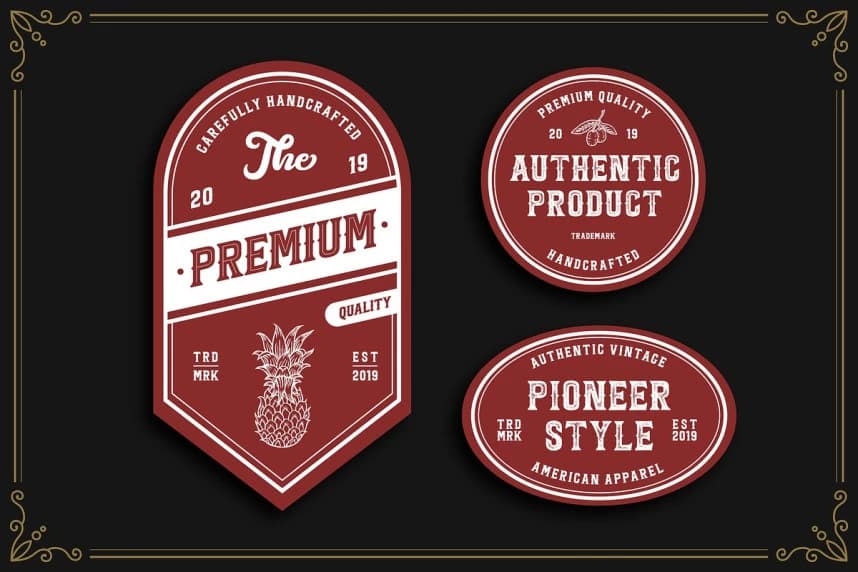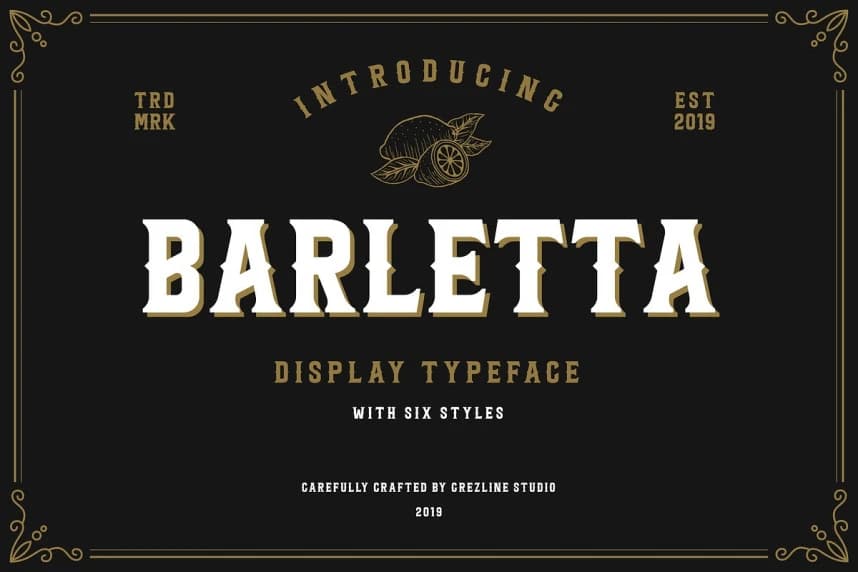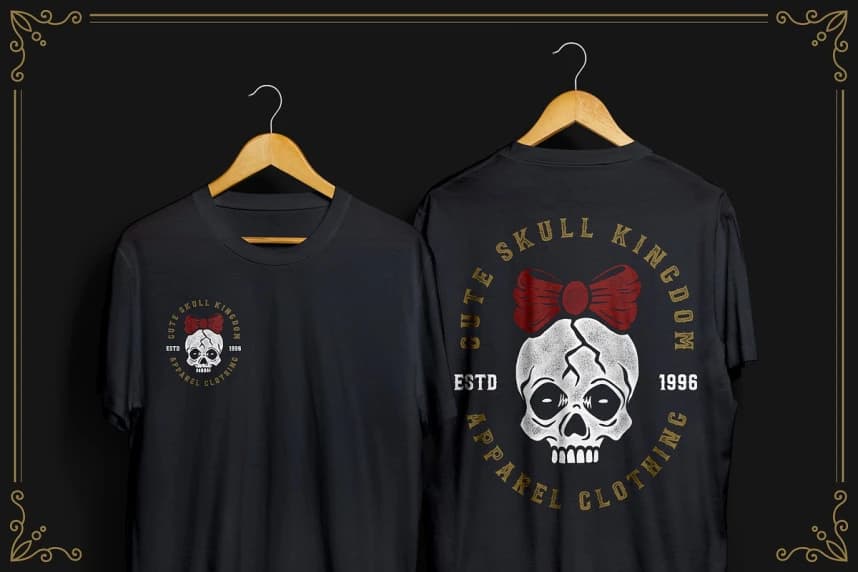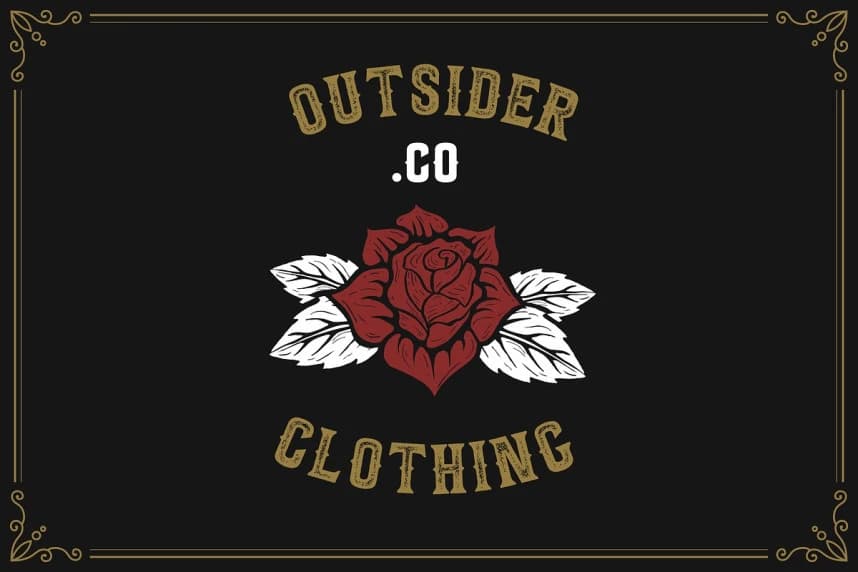
Barletta Font - batı esintili ve temiz görünümlü, yeni, taze ve benzersiz bir serif fontudur. Barletta'yı çok dikkatli bir şekilde, minimum ankraj noktasıyla tasarladım; böylece temiz ve ergonomik görünmesini sağladım. Tasarımlarınıza Barletta Font ile otantik ve estetik bir hava katın.
Barletta Font - batı esintili ve temiz görünümlü yeni, taze ve özgün bir serif fontudur. Barletta Font'ı minimum ankraj noktası kullanarak çok dikkatli biçimde tasarladım; temiz ve ergonomik görünmesini sağlamak için. Tasarımlarınıza Barletta Font ile özgün ve estetik bir hava katın.